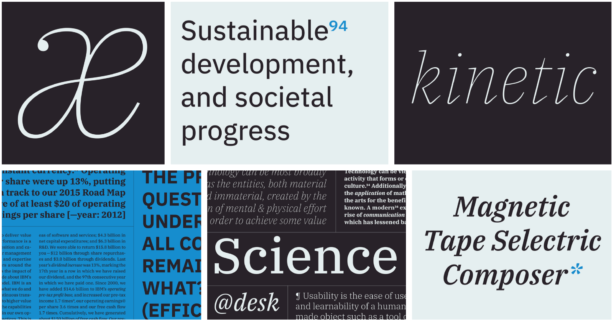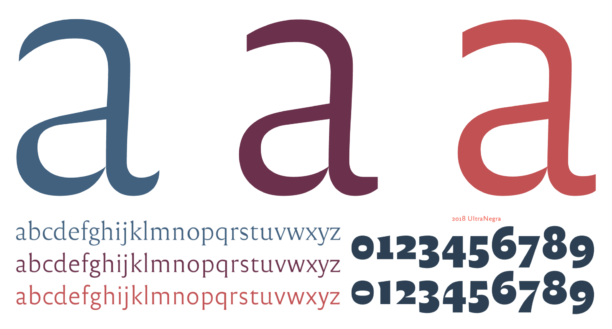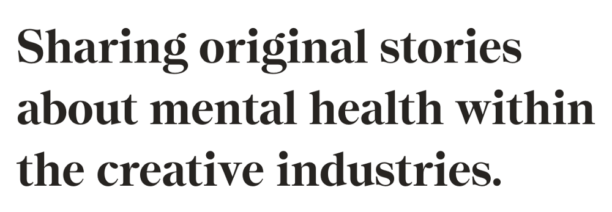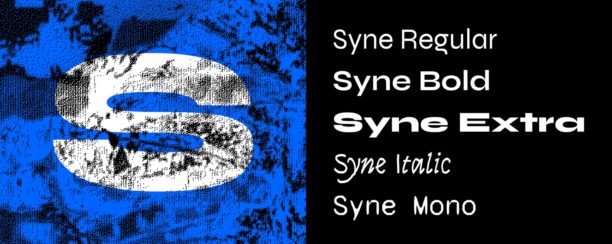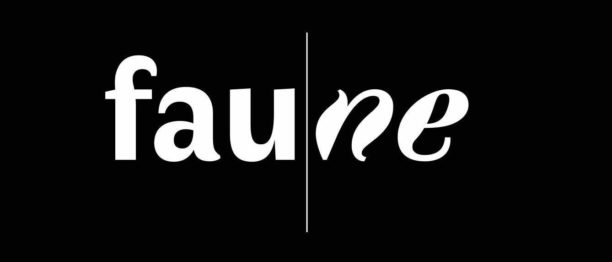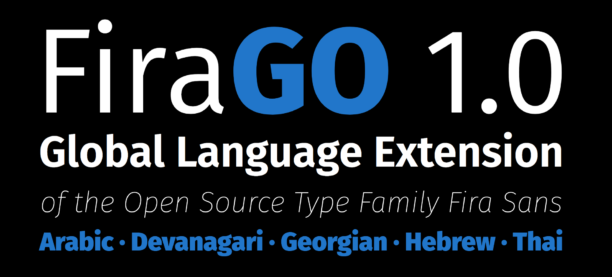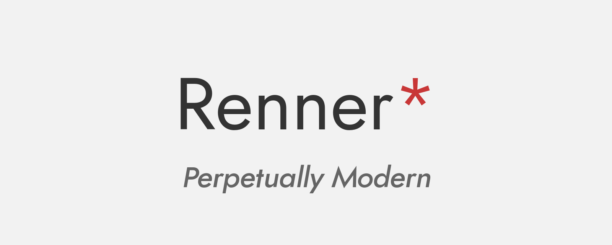
30 typographies gratuites pour un usage commercial
Une belle police de caractère est indispensable à un projet réussi. Il existe de nombreuses polices de qualité, mais celles-ci sont très souvent payantes. Noemi Stauffer de Fresh Fonts vient de publier une sélection de 30 typos libres de droits ou gratuites d’excellente qualité. Ce sont souvent des typos célèbres utilisées par des marques telles qu’IBM ou l’INRIA ou des polices de typographes reconnus. Toutes ces typographies sont utilisables pour un usage personnel ou commercial. Ce sont uniquement des polices mises à disposition récemment, sous licence Open Source ou gratuites.
IBM Plex
La nouvelle typo corporate d’IBM est disponible gratuitement sous licence Open source. À télécharger sur ce lien.
INRIA
L’Institut national de recherche en informatique et en automatique a commandé une nouvelle typo à l’occasion de ses 50 ans. Elle est aujourd’hui disponible gratuitement et en Open Source.
Reforma
Source Sans Variable et Source Serif
Syne
Faune
FiraGO
Renner